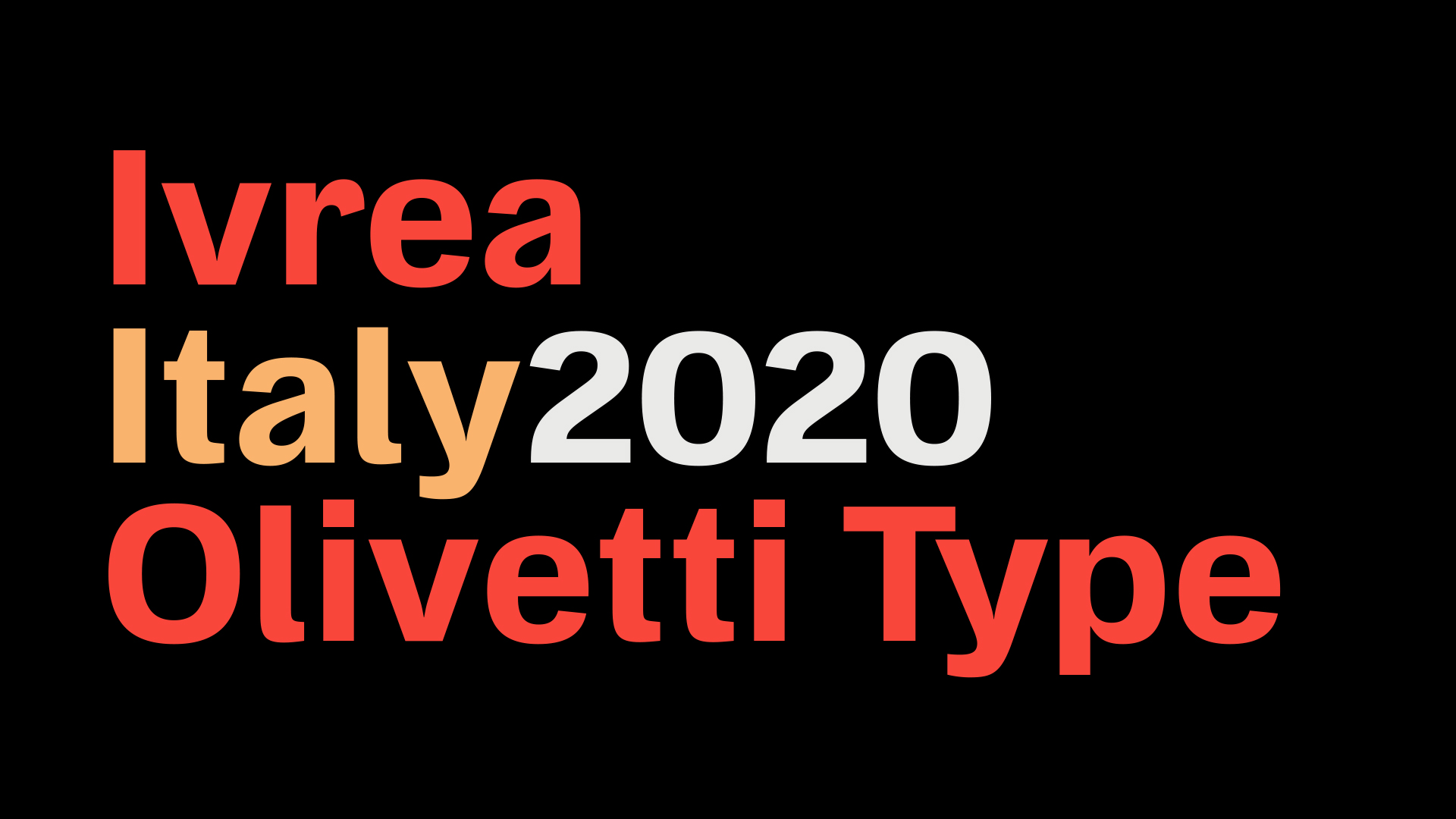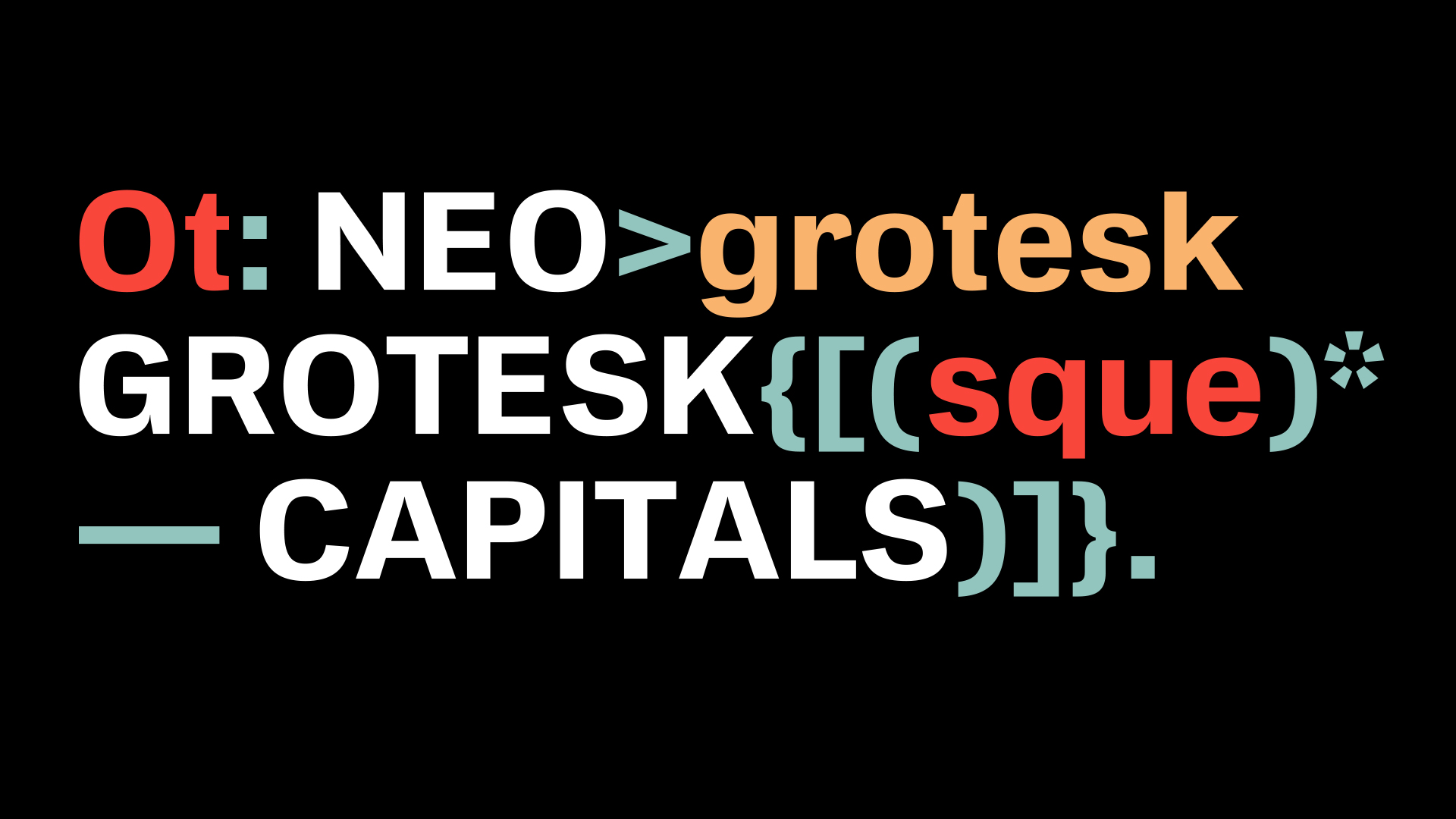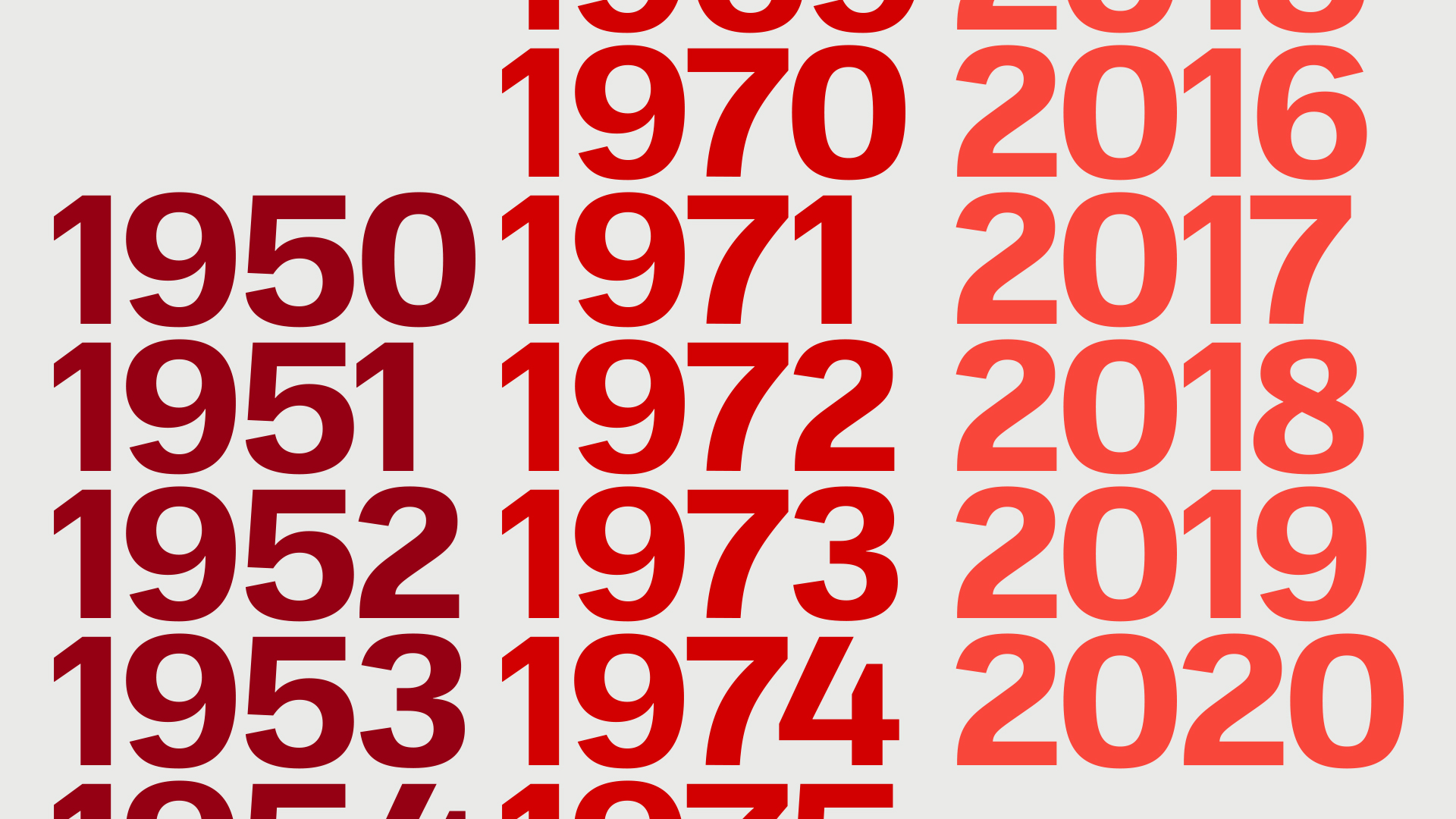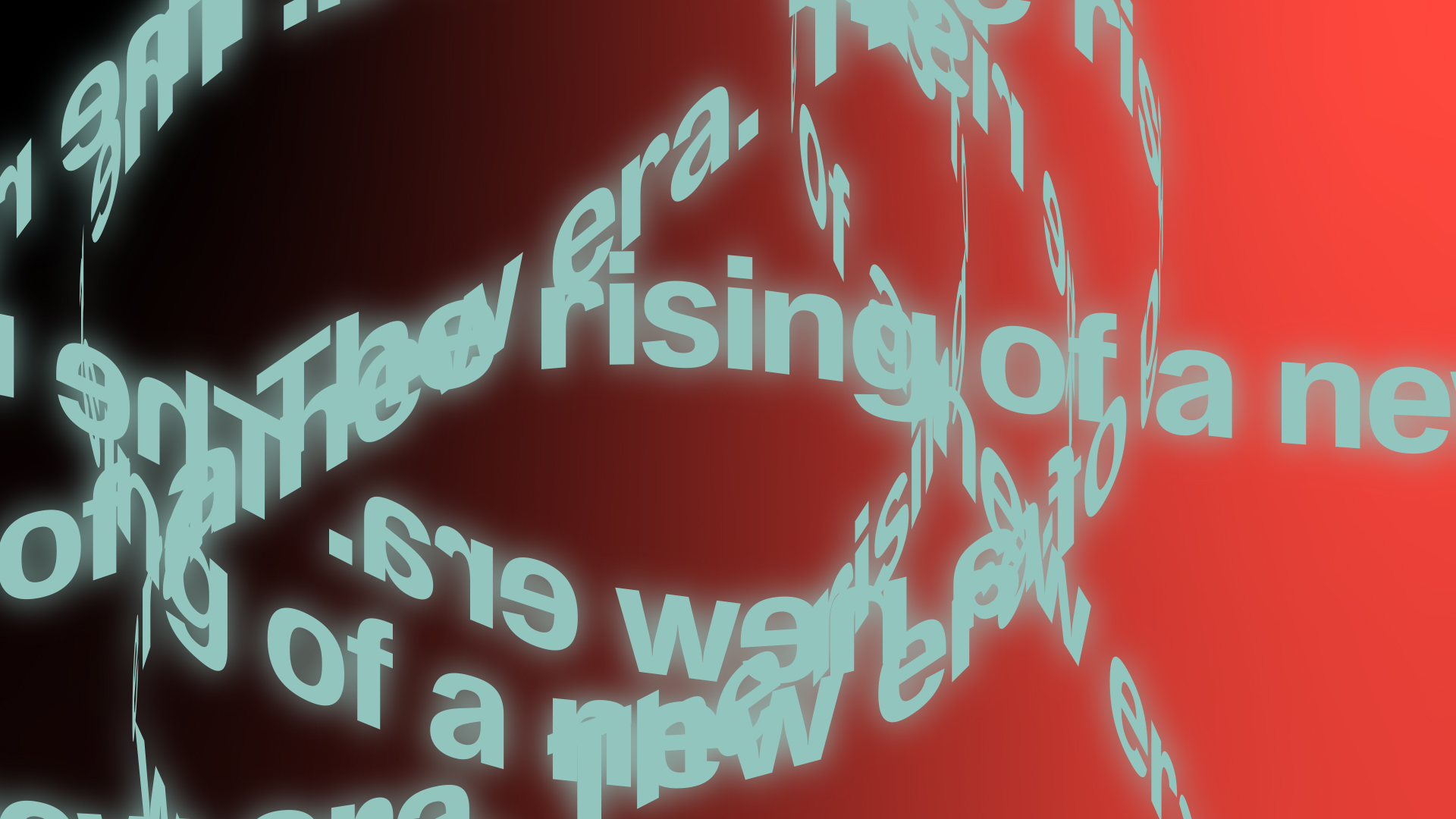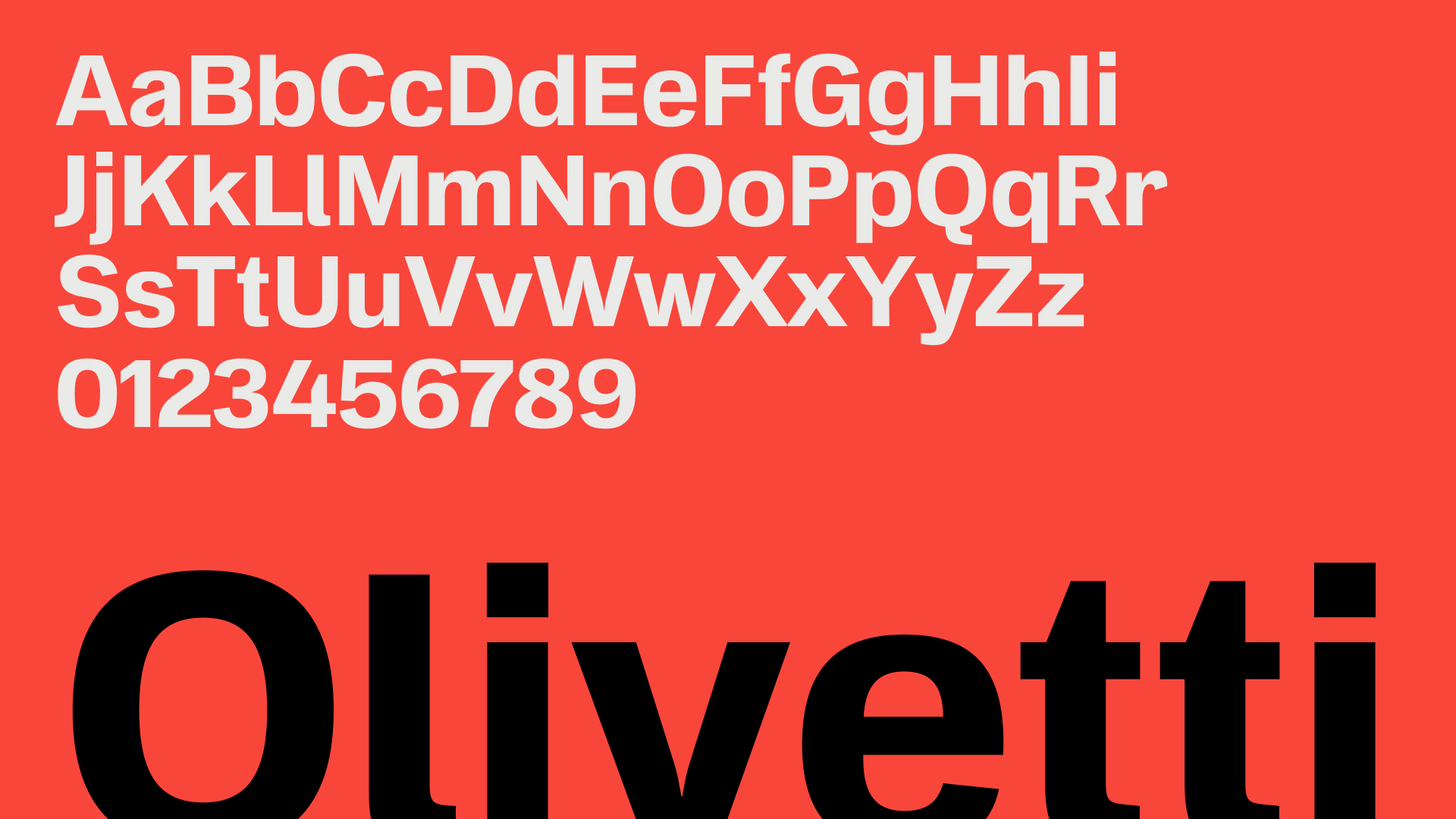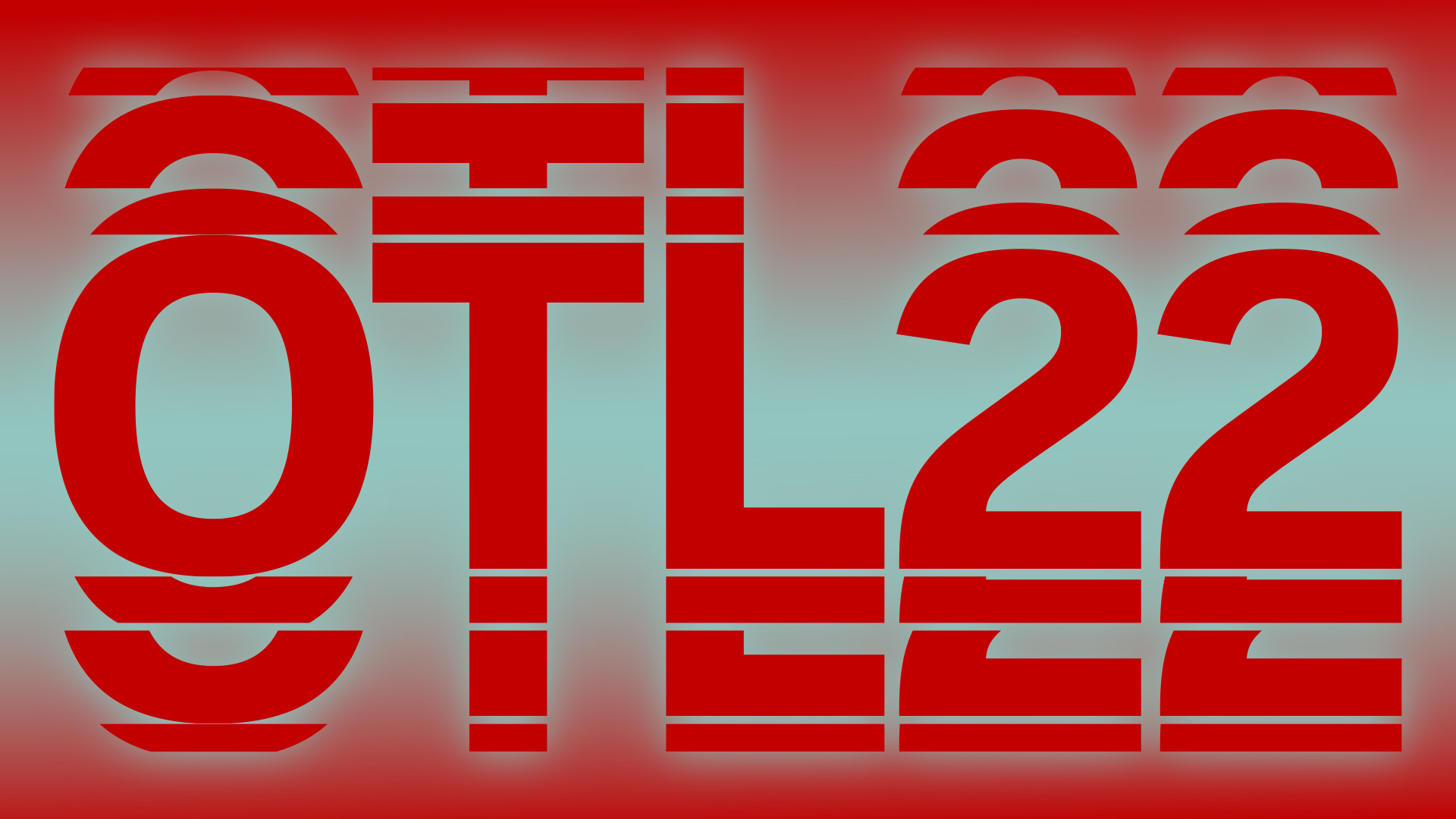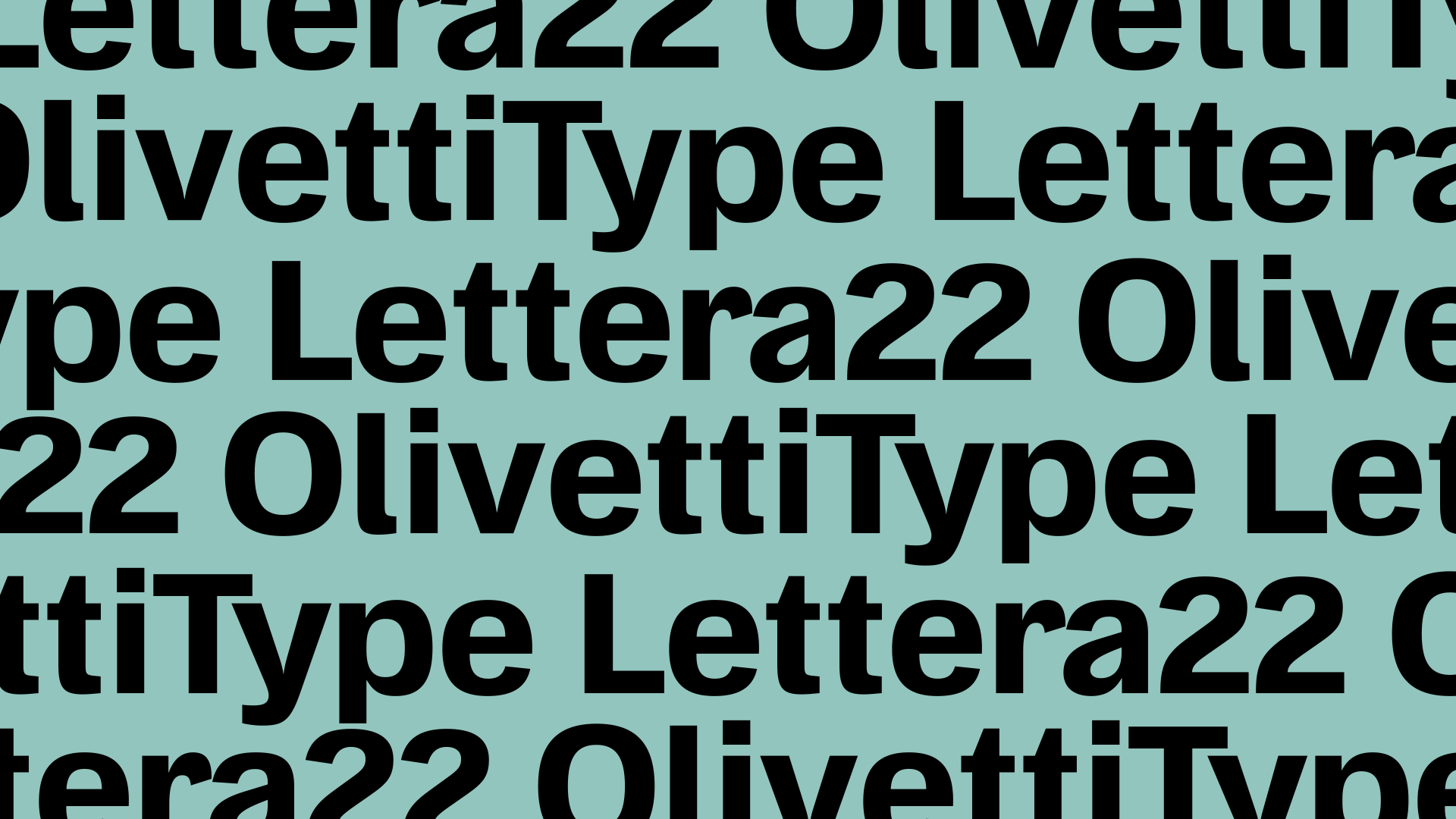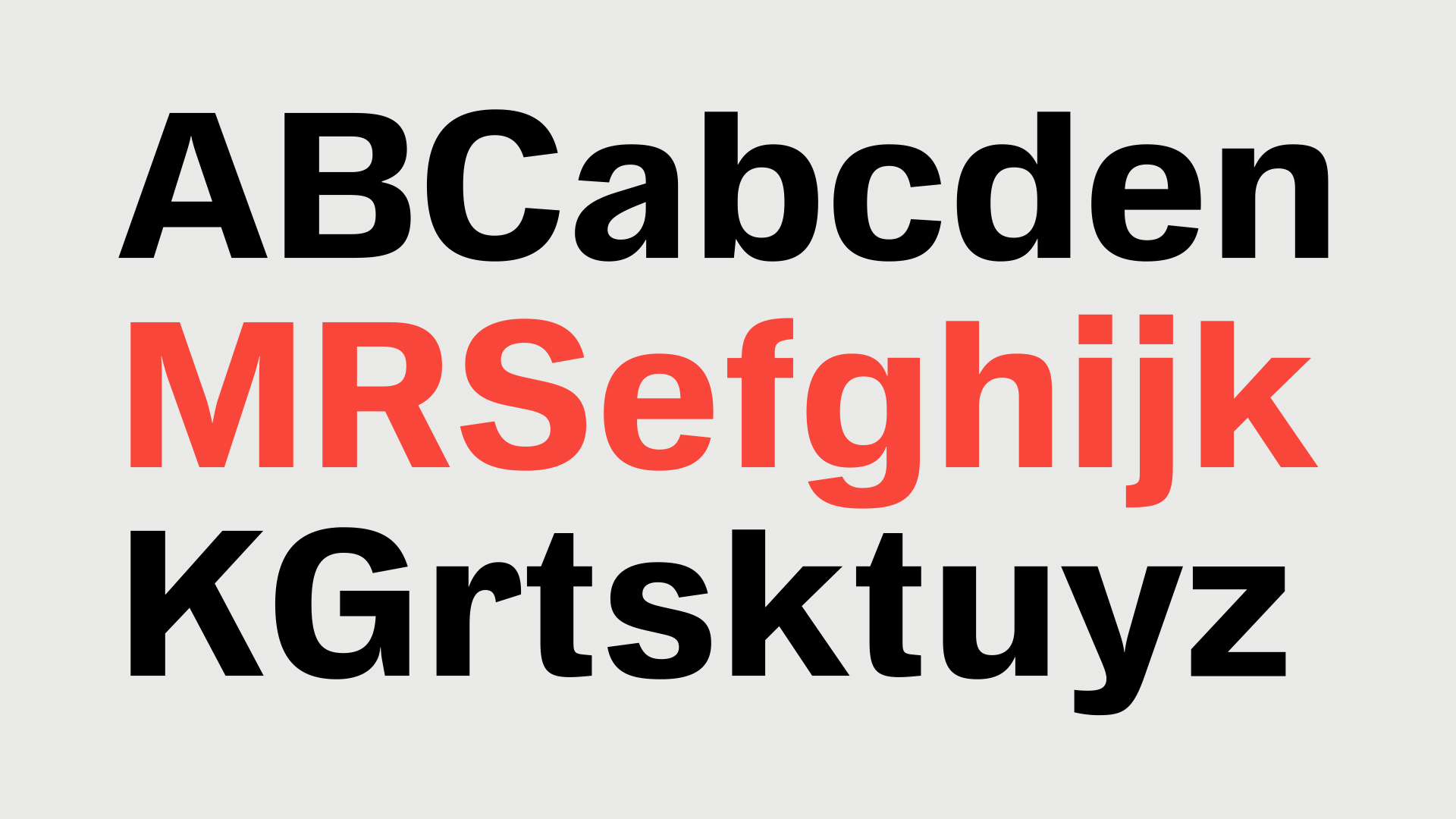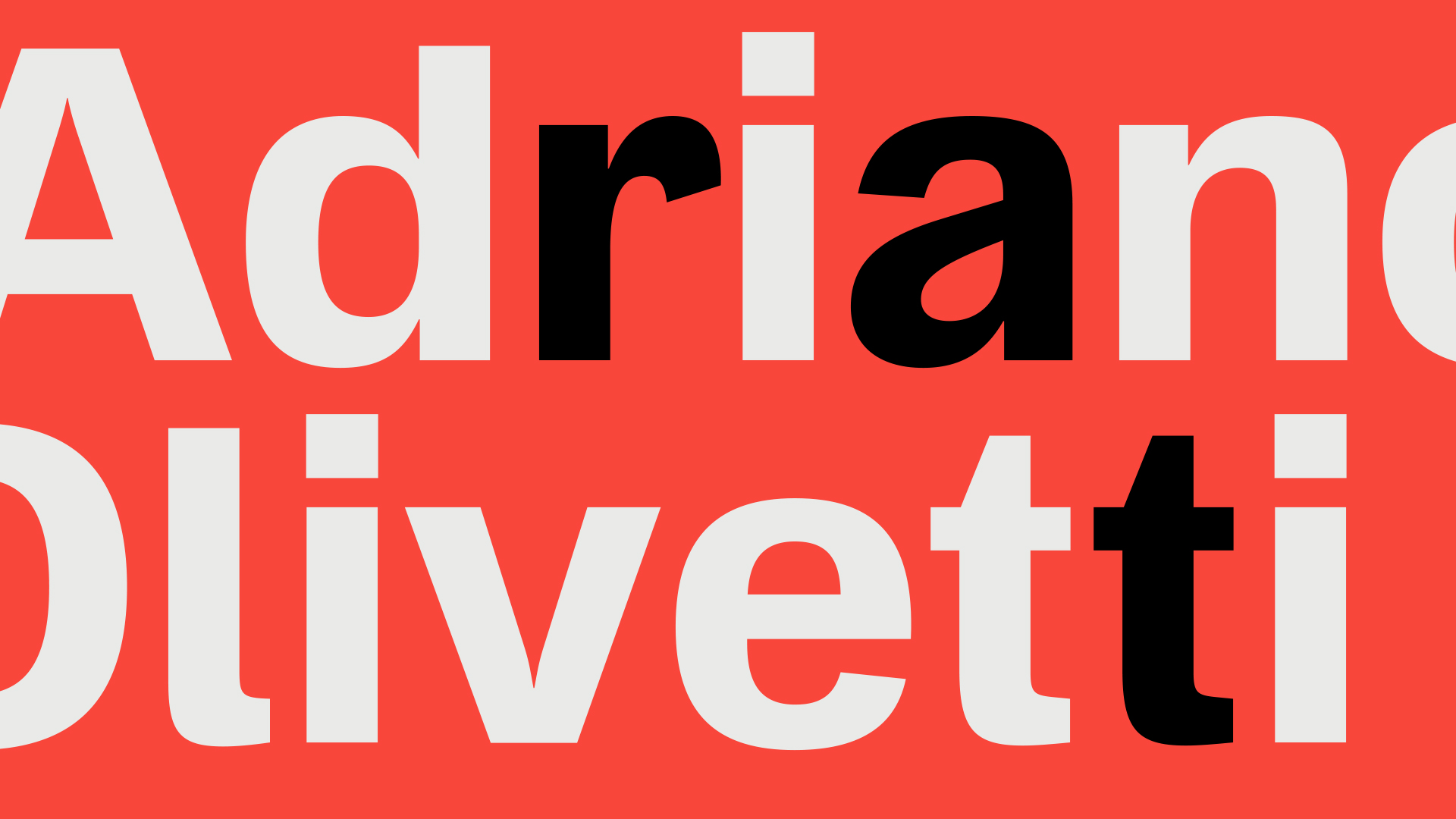
OT L22 es la nueva fuente dedicada al mundo Olivetti y al «mood» de la icónica máquina de escribir Lettera 22. Ideada y realizada por el 70 aniversario de la Lettera 22 con el objetivo de celebrar el «Made in Italy» junto con el estilo Olivetti. Hoy en día, la nueva fuente OT L22 es capaz de hacer revivir los valores fundamentales de Olivetti para reescribir, literalmente, la historia.
La fuente OT L22 en su versión Variable, es apta para todos los dispositivos. Está diseñada con Open Type Format y Web Open Font Format para usarse en cualquier medio digital e impreso. Desde un punto de vista tipográfico, la OTL 22 entra en la categoría de caracteres «grotescos» y «góticos» de finales del siglo XIX que han influido desde su creación en el estilo de comunicación de la empresa. El proceso de diseño de la fuente recorrió el pensamiento general de Giovanni Pintori partiendo de las raíces de lo grotesco, pasando por el análisis de la identidad tipográfica de Olivetti y atravesando el funcionalismo del siglo XX. El resultado es el carácter OT L22: la máxima expresión de un periodo y de una visión que han marcado la historia de las empresas italianas y del diseño. El «lettering» presenta una forma ovoide compuesta por letras compactas capaces de comunicar estabilidad manteniendo un importante impulso hacia arriba: un indicador del componente innovador típico de la empresa Olivetti.
«Con el nuevo diseño de la fuente OT L22 queremos unir muchos elementos de nuestra historia: desde la tradición hasta la innovación para comunicar hoy en digital y seguir hablando desde la comunidad a la comunidad»
Gaetano di Tondo, Presidente de Associazione Archivio Storico Olivetti, Vicepresidente, Director de Comunicación y Relaciones Externas de Olivetti
«Para un diseñador, diseñar para Olivetti es un gran honor porque, además de compartir los valores de una comunidad y de una empresa, se acerca a esos grandes nombres del diseño que han hecho historia»
Emanuele Cappelli, Fundador y Director creativo de Cappelli Identity Design
La historia del diseño.
Escrito con un nuevo carácter.